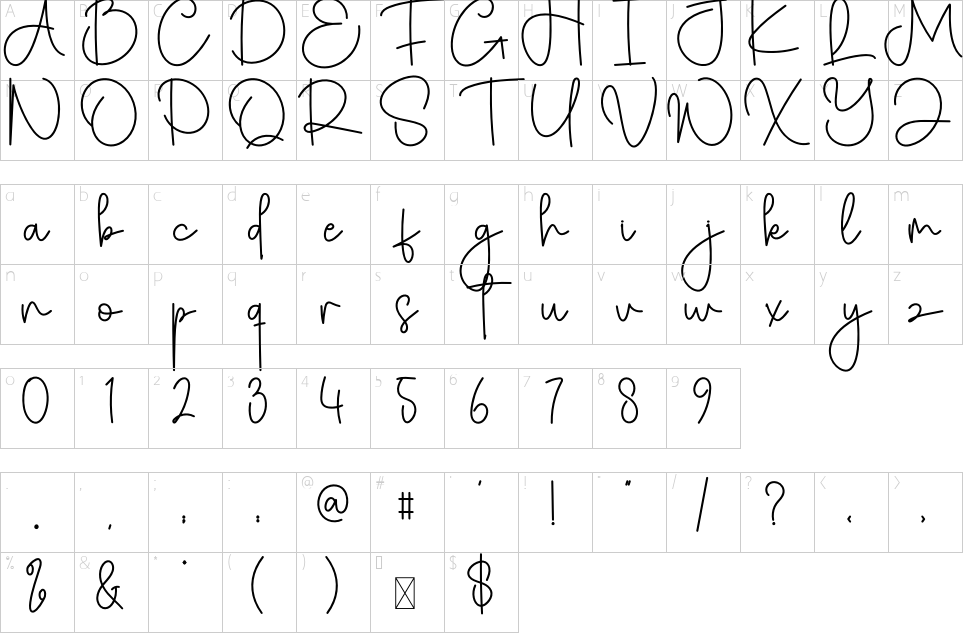
A fonte Pretty Girl é uma opção perfeita para aqueles que desejam adicionar um toque feminino e delicado a suas criações digitais. Desenhada pelo designer não informado, essa font oferece um estilo encantador e elegante que se adequa perfeitamente a textos em design gráfico, marketing, e até mesmo para criar elementos decorativos. Se você está procurando por uma font que seja tanto elegante quanto divertida, Pretty Girl é um ótimo lugar para começar. Com seu design cuidadoso e seu estilo único, Pretty Girl foi baixada 206 vezes e se tornou uma escolha popular para designers gráficos que desejam criar uma atmosfera agradável e atraente em seus projetos. É uma fonte gratuita para quem busca uma aposta segura em qualidade e estilo.